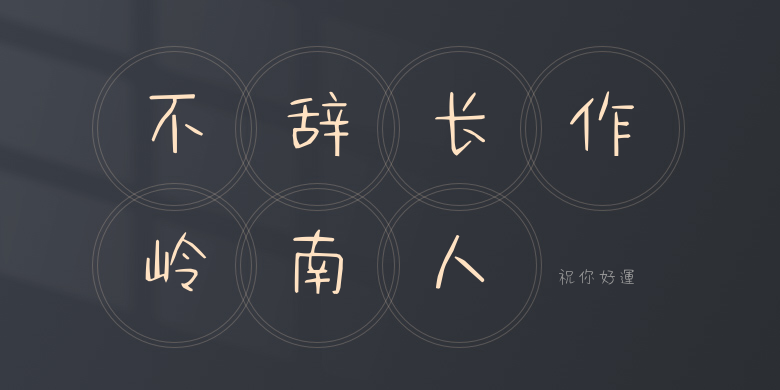
祝你好運
祝你好運,这款字体结构工整、笔画清晰,兼顾美观与易读性,适用于标题、正文、海报、包装、LOGO 等多种场景。字形优雅稳定,风格百搭耐看,适配日常排版与创意设计,让文字呈现更舒适、更具质感。祝你好運一笔一画,皆是细节,以均衡的比例、流畅的线条打造舒适视觉体验,字形端正大气,风格简约现代。无论是商业设计、品牌宣传还是日常排版,都能轻松驾驭,让文字更有格调与力量。祝你好運字体下载。